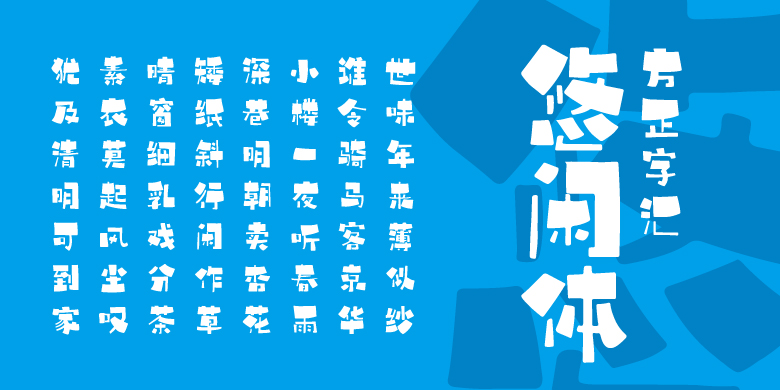
方正字汇-悠闲体
黄永刚
创意字体
采菊东篱下,悠然见南山。家住苍烟落照间,丝毫尘事不相关。月下风前,逍遥自在,兴则高歌困则眠。方正字汇-悠闲体,笔画随性而至,忽大忽小,忽疏忽密,大小落有致,来表现生活中的闲情雅致,不必忧心工作,不必烦恼人情,只消一盏清茶,或者一瓶喜爱的饮料,读书也好,听歌也行,刷刷手机都可以……无忧无虑的度过悠闲的一天,悠哉生活,亦是每个人追求的诗与远方。